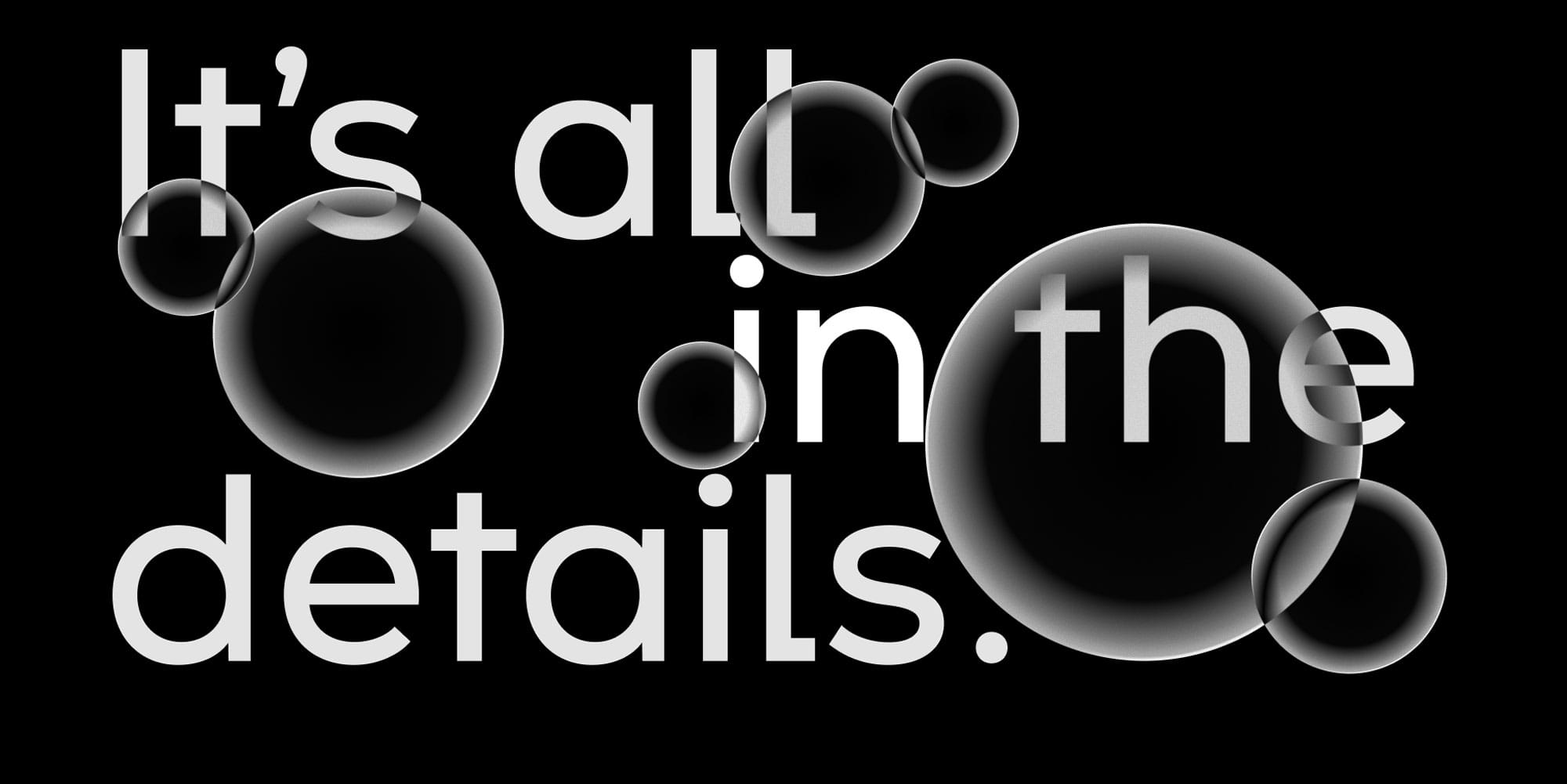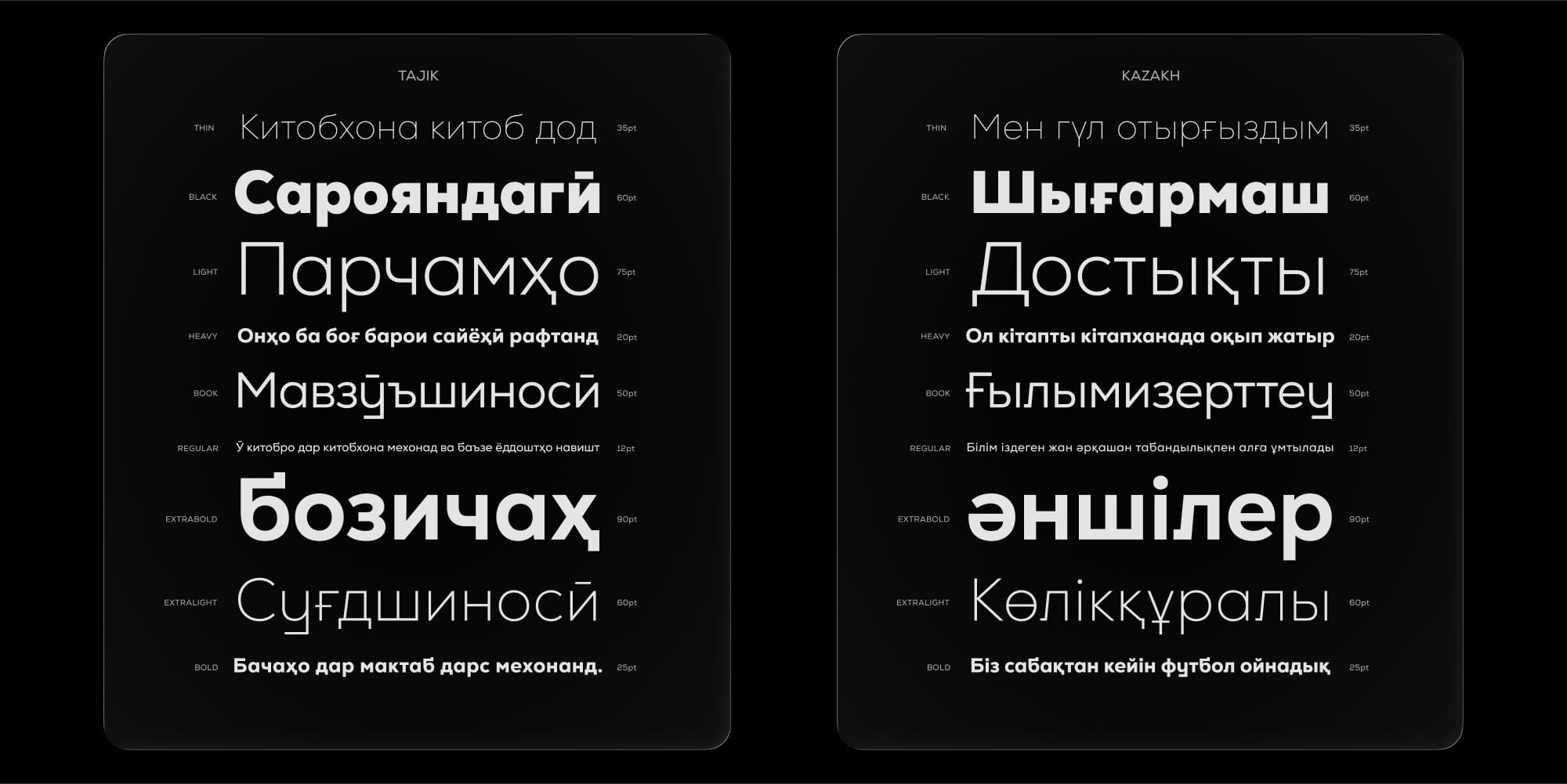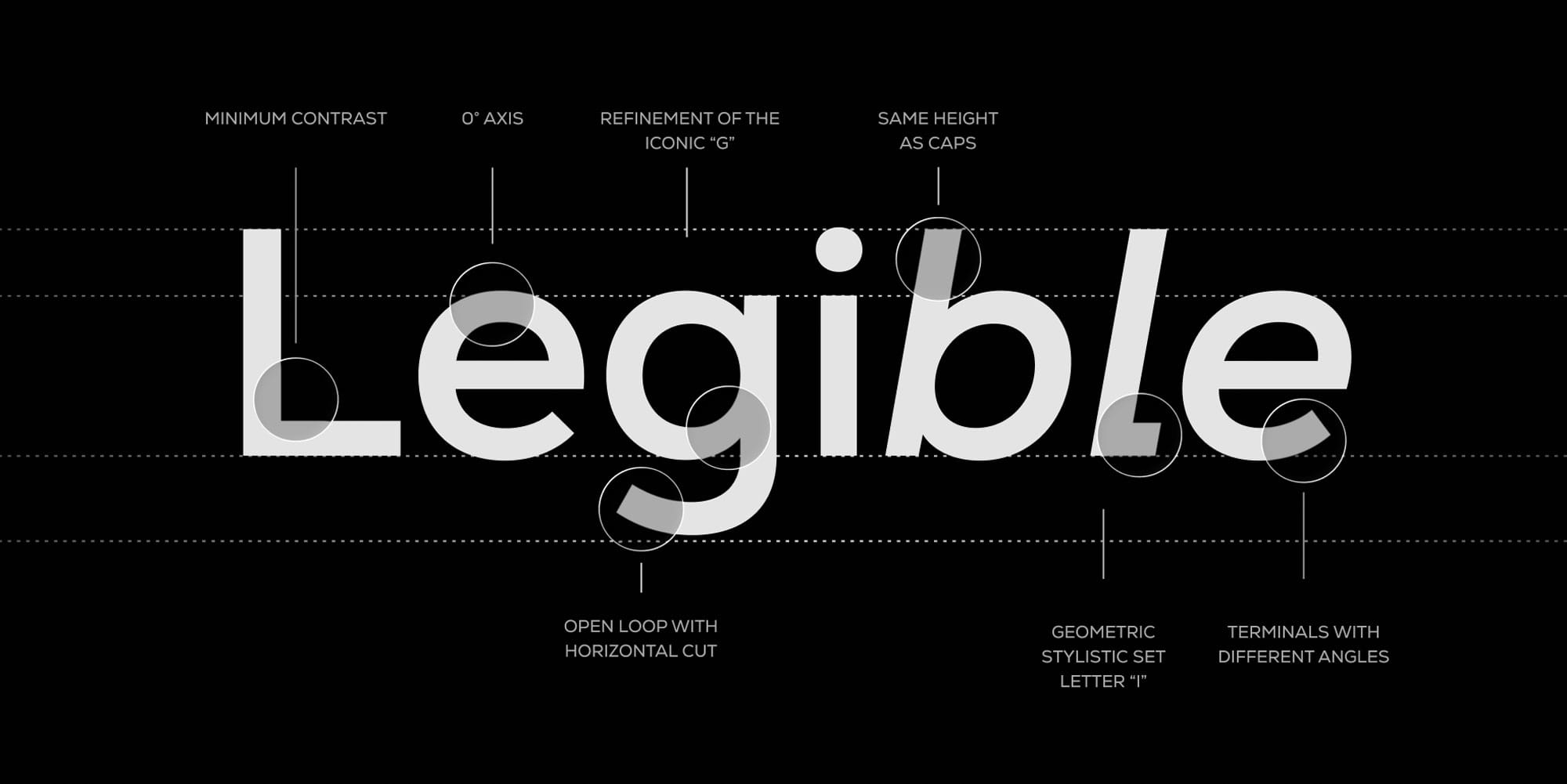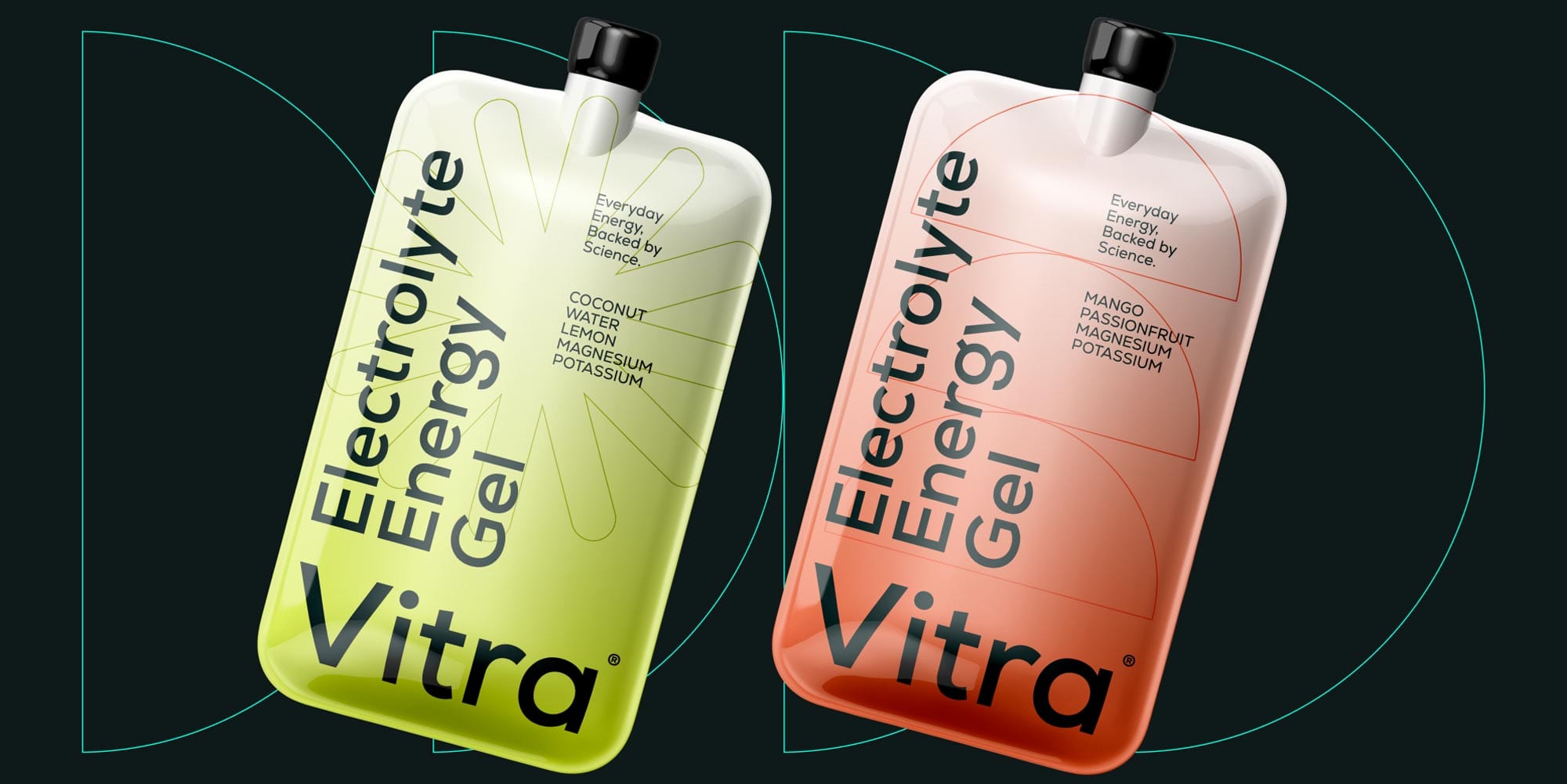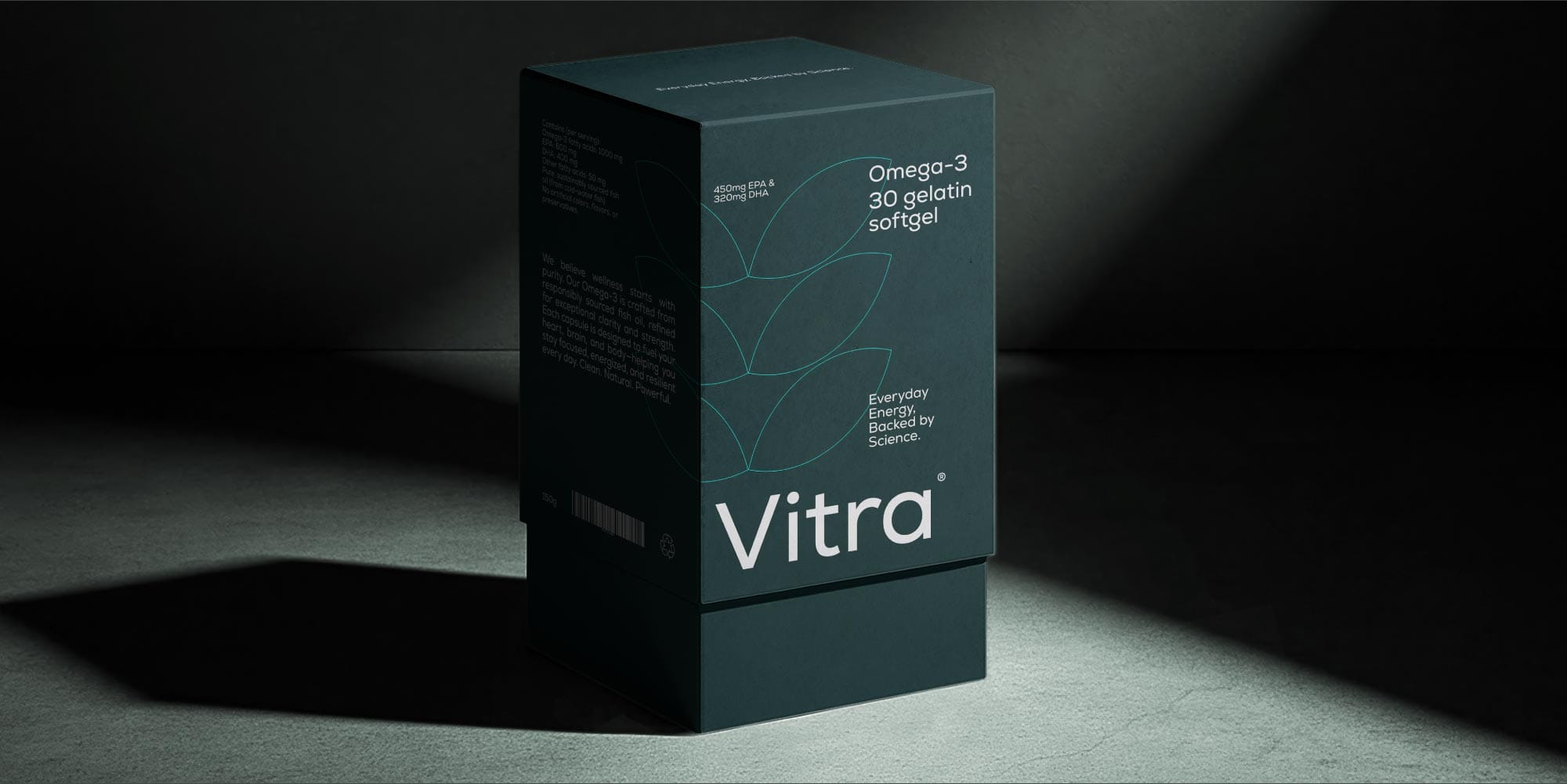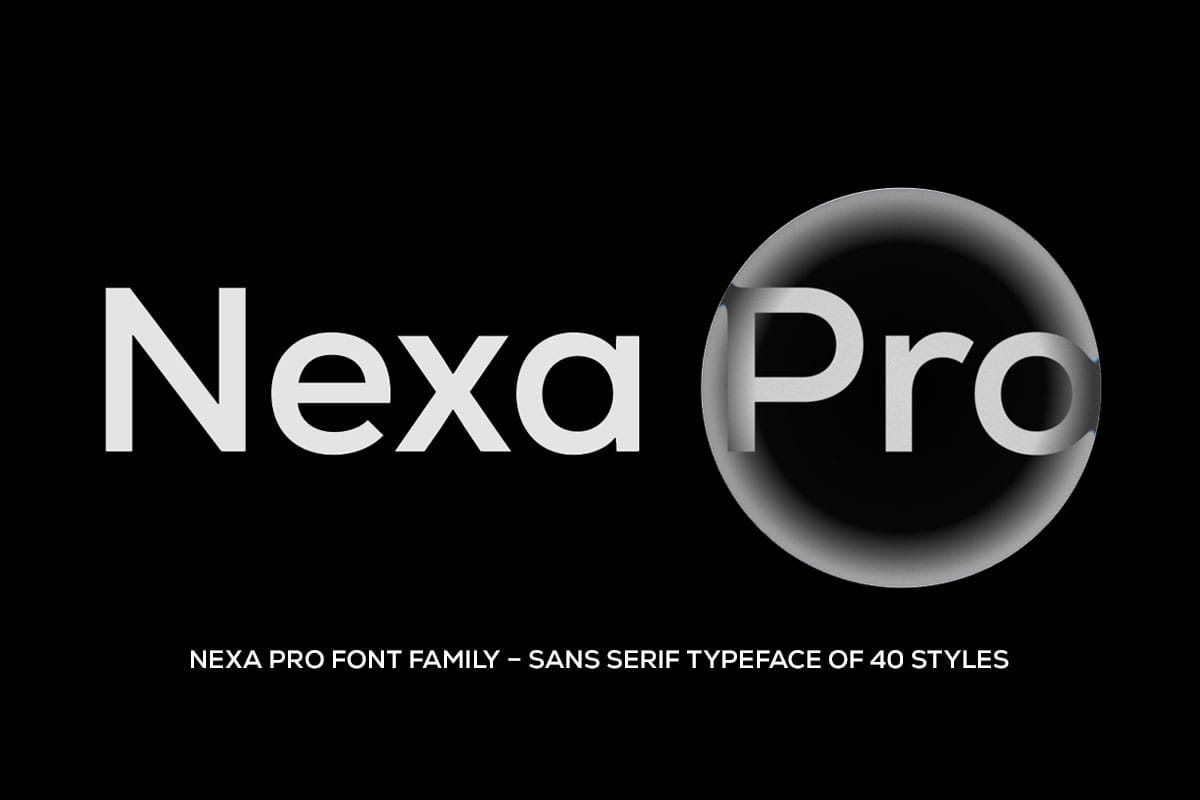
Nexa Pro Font Family – Sans Typeface of 40 Styles
Nexa Pro font là phiên bản nâng cấp của font Nexa kinh điển, được phát triển bởi Fontfabric. Ra mắt chính thức vào ngày 10/10/2025, Nexa Pro mang đến một hệ thống font geometric sans-serif tinh tế, kết hợp giữa sự hiện đại và độ đọc vượt trội. Không giống như các font geometric truyền thống ckhác, Nexa Pro thêm các đường cong tinh tế để tạo cảm giác gần gũi, phù hợp cho cả branding cao cấp lẫn sử dụng cho văn bản hàng ngày.
Theo nhà thiết kế Svet Simov, Nexa Pro được xây dựng với triết lý “evergreen” – bền vững theo thời gian, giúp thương hiệu của bạn luôn tươi mới mà không lỗi mốt. Với hơn 40 styles và hỗ trợ variable, đây là công cụ lý tưởng cho các dự án thiết kế web, branding logo hay UI/UX app.
Đặc điểm nổi bật của Nexa Pro
Điều làm nên sức hút của Nexa Pro chính là sự cân bằng hoàn hảo giữa hình thức và chức năng. Dưới đây là những tính năng chính:
- Cấu trúc geometric tinh tế: Dựa trên hình học cơ bản nhưng được tinh chỉnh đường cong và khoảng trắng để tăng độ rõ nét ở mọi kích thước. Phiên bản Display dành cho tiêu đề lớn, trong khi Text tối ưu cho đoạn văn dài.
- Hỗ trợ opentype nâng cao: Bao gồm ligatures, small caps, oldstyle figures, slashed zero, và hàng trăm ký tự currency/symbols – lý tưởng cho thiết kế tài chính hoặc đa quốc gia.
- Variable font: Cho phép điều chỉnh trọng lượng mượt mà, giúp tối ưu hóa tốc độ tải web mà không cần tải nhiều file.
- Hỗ trợ ngôn ngữ rộng rãi: Latin mở rộng, Cyrillic (bao gồm Kazakh), Greek, và đặc biệt có hỗ trợ đầy đủ dấu tiếng Việt.
So với bản Nexa gốc, Nexa Pro cải tiến đáng kể về độ đọc (legibility) và mở rộng script, giúp nó phù hợp hơn cho các dự án global như ứng dụng di động hoặc chiến dịch quảng cáo quốc tế.